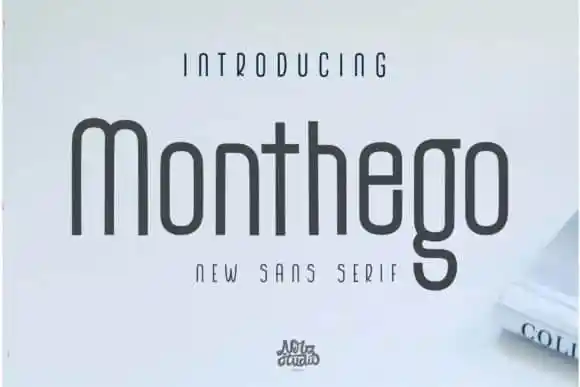
The Monthego Sans Serif Font – Download Grátis
A The Monthego Sans Serif Font é uma escolha elegante para projetos que buscam simplicidade e modernidade. Creada pela Nerdstudio, esta fonte é minimalista com linhas sólidas e bordas arredondadas. Seu formato único cria um visual casual e sofisticado, sem se aprofundar na finura ou grossura exagerada. O equilíbrio entre esses atributos faz desta uma opção versátil para diversos usos gráficos. Não é apenas a escolha perfeita para adicionar beleza aos teus projetos — ela também adiciona um toque moderno e casual ao seu design, tornando-a uma fonte que merece ser explorada.